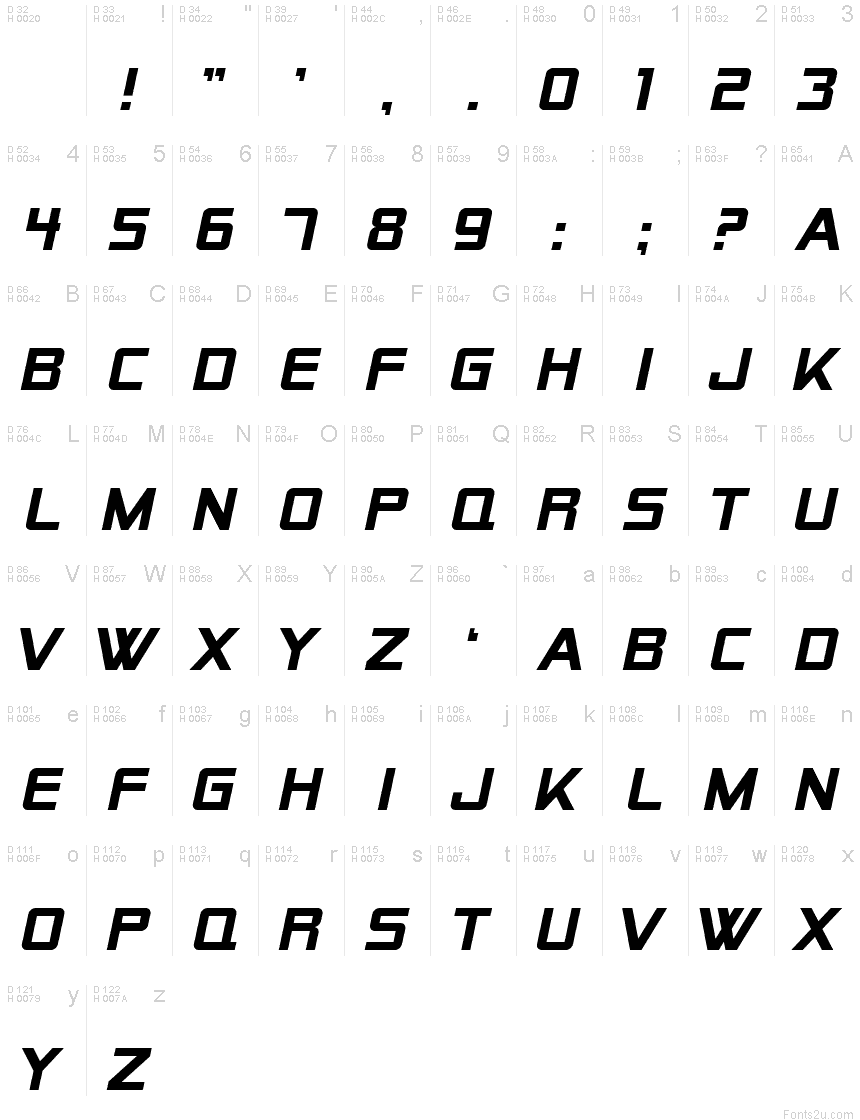
SF Alien Encounters Solid Italic von ShyFoundry ist eine kostenlose, futuristische Display-Schrift für Großbuchstaben mit starkem Sci-Fi-Einschlag. Die Buchstaben wirken wie aus dunklen, schnellen Formen gemeißelt – breite, kantige Striche, abgeschnittene Ecken und eine steile Neigung verleihen dem Alphabet diesen Look von Raumschiff-Paneelen und Techno-Vibes der späten 90er, weit entfernt von einem neutralen, modernen Erscheinungsbild.
Sie eignet sich perfekt für Spiele-Logos, Filmtitel, Musik-Cover, Plakatüberschriften und Stream-Grafiken, bei denen ein kostenloser Font sofort Sci-Fi-Atmosphäre braucht. Da die Großbuchstaben breit und scharf vereinfacht sind, passt sie auch hervorragend zu kurzen Marken-Slogans, Kapitelanfängen und Monogrammen, die schnell, synthetisch und irgendwie außerirdisch wirken sollen.